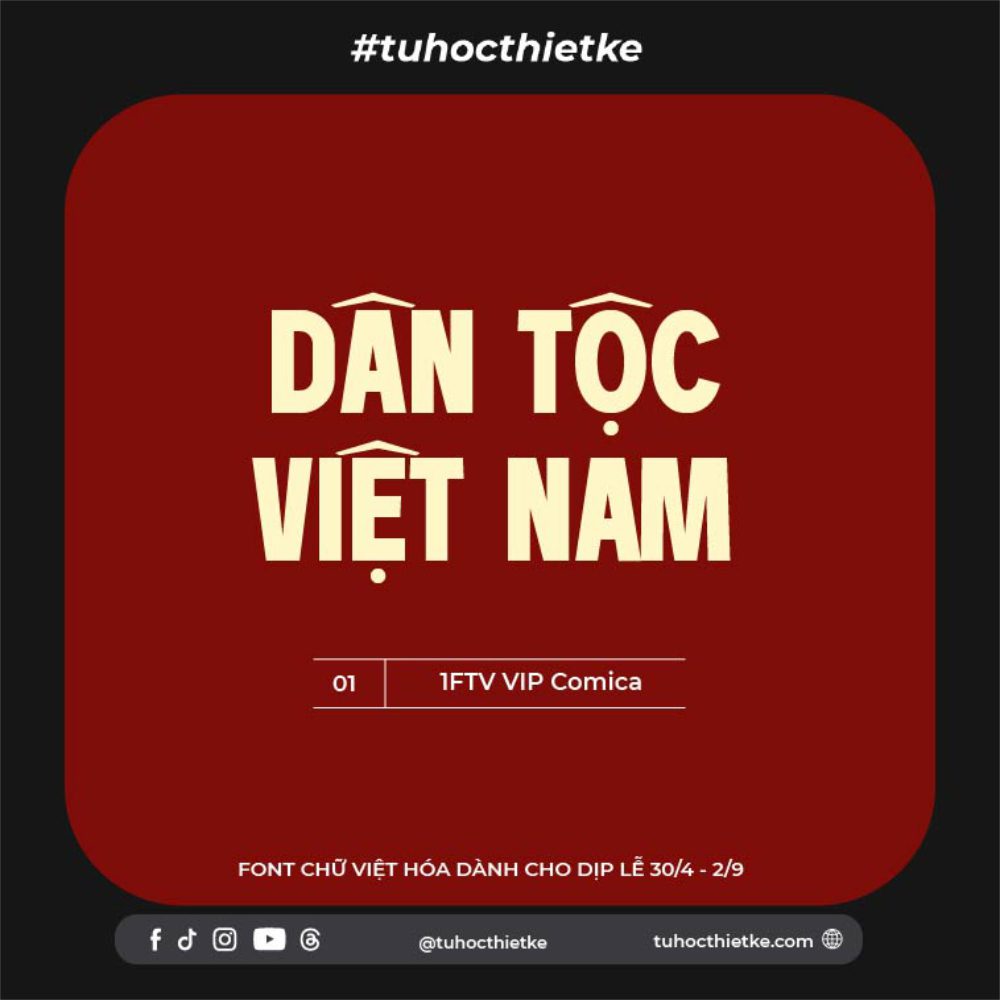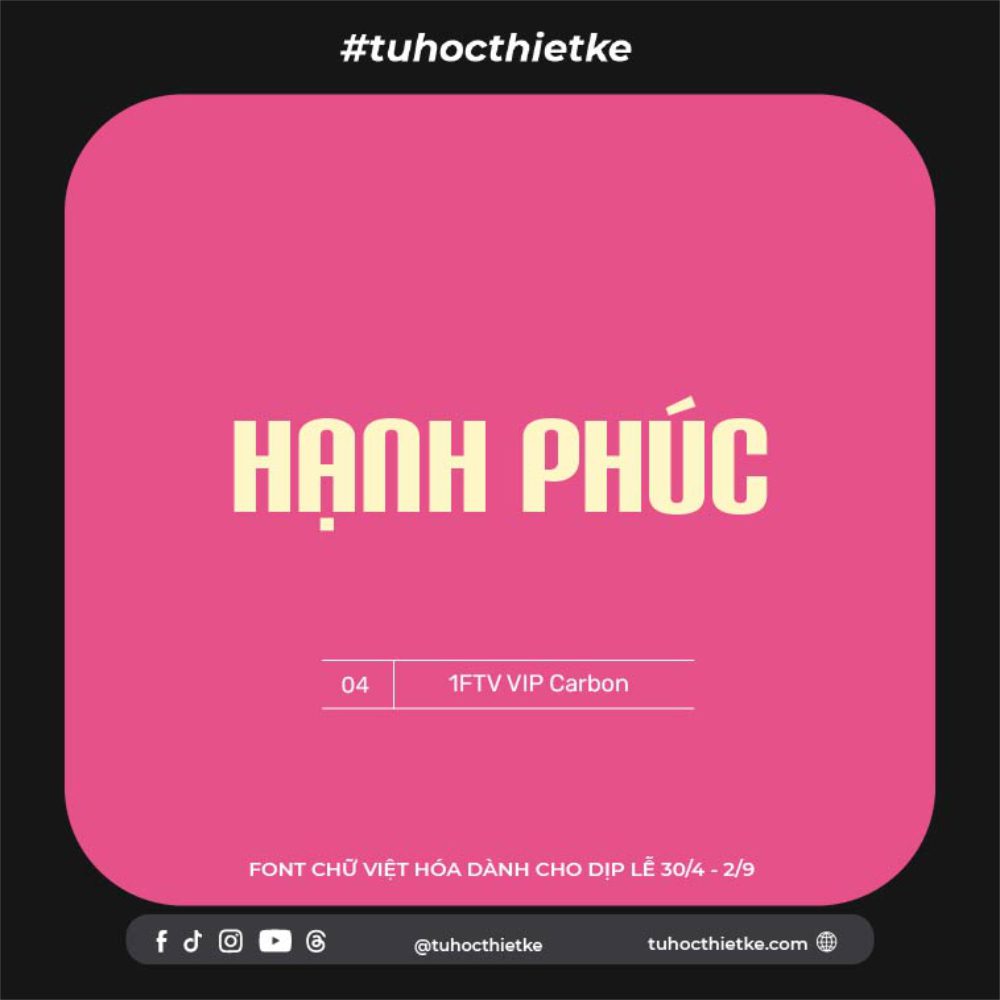
Font Việt Hóa dành cho dịp Đại lễ 30/4 và 2/9 là nguồn tài nguyên quan trọng đối với designer, content creator, marketer và những người thường xuyên thiết kế ấn phẩm truyền thông theo chủ đề lễ kỷ niệm, sự kiện quốc gia hoặc các chương trình đặc biệt. Trong những dịp mang ý nghĩa lịch sử lớn như Ngày Giải phóng miền Nam 30/4 và Quốc khánh 2/9, thiết kế không chỉ cần đẹp mắt mà còn phải thể hiện được tinh thần trang trọng, tự hào, hào hùng và phù hợp với không khí chung. Một bộ font chữ phù hợp sẽ giúp poster, banner, backdrop, standee, thiệp mời, bài đăng mạng xã hội hoặc ấn phẩm quảng bá trở nên nổi bật và truyền tải thông điệp hiệu quả hơn.
Vì Sao Cần Chọn Font Phù Hợp Cho Dịp 30/4 và 2/9?
Trong thiết kế, font chữ không chỉ dùng để hiển thị nội dung mà còn góp phần tạo cảm xúc cho người xem. Với các thiết kế phục vụ dịp đại lễ, font chữ cần thể hiện được sự trang nghiêm, mạnh mẽ và rõ ràng. Nếu chọn sai font, thiết kế có thể trở nên thiếu chuyên nghiệp, khó đọc hoặc không phù hợp với tinh thần của sự kiện.
Các dịp như 30/4 và 2/9 thường gắn với những thông điệp về lịch sử, đất nước, niềm tự hào dân tộc, sự đoàn kết và tinh thần tri ân. Vì vậy, designer nên ưu tiên các kiểu chữ có bố cục chắc chắn, nét chữ rõ ràng, dễ đọc và có khả năng tạo điểm nhấn tốt. Một font chữ phù hợp sẽ giúp tiêu đề nổi bật hơn, đồng thời làm cho tổng thể thiết kế trở nên hài hòa và đúng chủ đề.
Font Việt Hóa Là Gì?
Font Việt Hóa là những font chữ đã được bổ sung hoặc chỉnh sửa để hỗ trợ đầy đủ các ký tự tiếng Việt có dấu. Đây là yếu tố rất quan trọng khi thiết kế tại Việt Nam, bởi nhiều font nước ngoài dù đẹp nhưng lại không hiển thị đúng các dấu như sắc, huyền, hỏi, ngã, nặng hoặc các ký tự đặc trưng như ă, â, ê, ô, ơ, ư, đ.
Khi sử dụng font đã Việt hóa, designer có thể yên tâm dùng cho tiêu đề, slogan, nội dung phụ hoặc thông tin sự kiện mà không lo lỗi dấu. Đặc biệt với các ấn phẩm dành cho dịp 30/4 và 2/9, nội dung thường mang tính trang trọng và được sử dụng rộng rãi, nên việc hiển thị đúng tiếng Việt là điều bắt buộc để đảm bảo sự chỉn chu.
Những Kiểu Font Phù Hợp Cho Thiết Kế Đại Lễ
Font serif trang trọng
Font serif là nhóm font có chân, thường mang lại cảm giác cổ điển, nghiêm túc và sang trọng. Đây là lựa chọn phù hợp cho các thiết kế có tính trang nghiêm như poster kỷ niệm, backdrop hội trường, thiệp mời sự kiện, banner chương trình hoặc các ấn phẩm truyền thông chính thức.
Với các dịp 30/4 và 2/9, font serif có thể giúp tiêu đề trở nên vững chắc, lịch sự và giàu tính biểu tượng. Khi kết hợp cùng các gam màu như đỏ, vàng, trắng hoặc xanh đậm, font serif sẽ tạo cảm giác trang trọng và phù hợp với không khí đại lễ.
Font sans-serif hiện đại
Font sans-serif là nhóm font không chân, có ưu điểm dễ đọc, gọn gàng và hiện đại. Đây là lựa chọn rất phù hợp cho các thiết kế truyền thông online, infographic, bài đăng mạng xã hội, banner website hoặc các ấn phẩm cần truyền tải thông tin nhanh.
Trong thiết kế đại lễ, font sans-serif thường được dùng cho nội dung phụ như thời gian, địa điểm, mô tả chương trình hoặc các dòng thông tin ngắn. Khi kết hợp với một font tiêu đề mạnh mẽ, font sans-serif giúp bố cục trở nên cân bằng, rõ ràng và dễ theo dõi hơn.
Font display mạnh mẽ
Font display là nhóm font có cá tính rõ rệt, thường được dùng cho tiêu đề lớn hoặc điểm nhấn chính trong thiết kế. Với chủ đề đại lễ, bạn có thể chọn các font display có nét chữ dày, dáng chữ vững, tạo cảm giác hào hùng và nổi bật.
Tuy nhiên, khi dùng font display, cần chú ý đến độ dễ đọc. Những font quá cầu kỳ hoặc quá nhiều chi tiết có thể gây rối mắt, đặc biệt khi đặt trên nền có hình ảnh, cờ, hoa văn hoặc hiệu ứng ánh sáng. Tốt nhất, hãy dùng font display cho tiêu đề ngắn và dùng font đơn giản hơn cho phần nội dung còn lại.
Ứng Dụng Font Trong Thiết Kế Dịp 30/4 và 2/9
Thiết kế poster, banner chào mừng
Poster và banner là những ấn phẩm được sử dụng nhiều trong các dịp đại lễ. Một tiêu đề rõ ràng, mạnh mẽ sẽ giúp người xem nhanh chóng nắm bắt chủ đề của thiết kế. Với các thông điệp như “Chào mừng Ngày Giải phóng miền Nam 30/4” hoặc “Mừng Quốc khánh 2/9”, font chữ nên có nét chắc, dễ đọc và phù hợp với bố cục tổng thể.
Designer có thể dùng font serif hoặc display cho phần tiêu đề chính, kết hợp font sans-serif cho thông tin phụ. Cách phối này vừa tạo điểm nhấn, vừa đảm bảo thiết kế không bị rối.
Thiết kế backdrop, standee và sân khấu
Đối với backdrop, standee hoặc các ấn phẩm khổ lớn, độ dễ đọc của font là yếu tố quan trọng hàng đầu. Người xem thường nhìn từ khoảng cách xa, vì vậy không nên dùng font quá mảnh, quá nghiêng hoặc có quá nhiều chi tiết trang trí.
Những font có nét đậm vừa phải, khoảng cách chữ tốt và hình dáng cân đối sẽ giúp nội dung rõ ràng hơn. Đặc biệt, các sự kiện kỷ niệm, hội nghị, lễ trao giải hoặc chương trình văn nghệ chào mừng cần sự trang trọng, nên font chữ cũng cần thể hiện được tinh thần này.
Thiết kế bài đăng mạng xã hội
Vào các dịp 30/4 và 2/9, nhiều thương hiệu, fanpage, cơ quan, trường học hoặc cá nhân thường đăng bài chúc mừng, thông báo lịch nghỉ, chương trình ưu đãi hoặc nội dung truyền thông. Khi đó, font chữ đóng vai trò quan trọng trong việc tạo sự thu hút trên Facebook, Instagram, Zalo hoặc website.
Khi lựa chọn font, bạn nên ưu tiên khả năng hỗ trợ tiếng Việt, độ dễ đọc, phong cách phù hợp với tinh thần đại lễ và giấy phép sử dụng rõ ràng. Một bộ font được tổng hợp kỹ lưỡng sẽ giúp quá trình thiết kế nhanh hơn, chuyên nghiệp hơn và tạo nên những ấn phẩm ấn tượng cho các dịp lễ quan trọng.